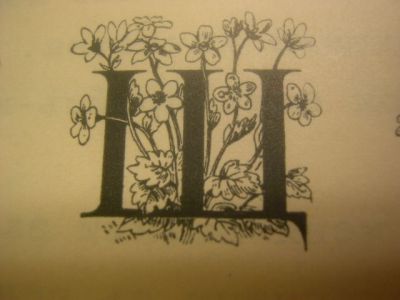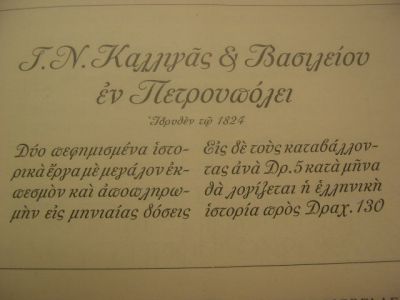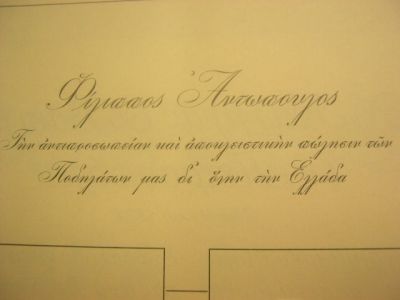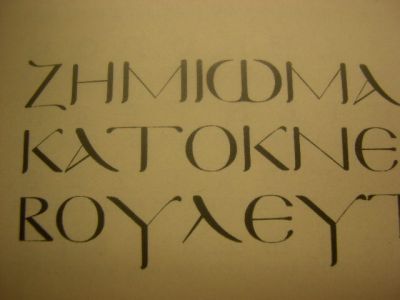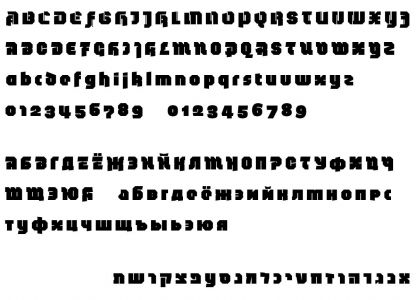
Griechische und kyrillische Schriften
ich bin auf der Suche nach kyrillischen und vorallem griechischen Schriften. In folgendem Bild seht ihr, welche Schriften ich für die jeweiligen Gruppen bereits gefunden habe:
(Ein größeres Bild gibt es hier.)
Eine griechische Egyptienne konnte ich nicht ausfindig machen. Aber die richtig großen Lücken klaffen bei den gebrochenen Schriften. Ganz besonders dürftig sieht es bei den griechischen Schriften aus. Leider habe ich noch keine Foundry eigens für griechische Schriften gefunden, so wie etwa ParaType für kyrillische Fonts.
Wenn jemand Foundries kennt, die auf griechische Schriften spezialisiert sind, lasst mich bitte nicht dumm sterben. Sollte jemand einen konkreten Font kennen, der eine Leerstelle auffüllen könnte, wäre ich für die Info noch tausendmal dankbarer.
Gibt es überhaupt sowas wie gebrochene griechische Schriften?
Historisch gesehen stellt sich diese Frage nicht nur für griechische, sondern auch für russische Schriften.
Ich habe gerade mal in meinen ältesten Schriftmuster-Büchern nachgeschaut von Schelter & Giesecke, der Bauerschen Gießerei und Klinkhardt: Es wurden sehr wohl griechische als auch russische Schriften angeboten, aber immer in Antiqua- oder Grotesk-Schnitten, auch als Schreibschriften. Aber nie als Gebrochene Schriften. Hebräische Schriften gab es übrigens auch. Und Aramäisch.
Ist nicht auch ein Widerspruch in einer Kombination Gebrochene Schrift <> Fremdsprachen-Zeichensatz? Nicht, daß es technisch nicht machbar (gewesen) wäre..
ja, es ist ein Widerspruch zwischen gebrochener und fremdsprachiger Schrift. Dennoch wurde er – zumindestens was das Kyrillische angeht – in der Vergangenheit bereits mehrfach aufgelöst; siehe die Beispiele aus meiner obigen Darstellung: »San Marco Cyr«, »Encient German Gothic« und »American Uncial«.
Gestern habe ich eine neuzeitliche Schrift gefunden (und mir selbst zu Ostern geschenkt), die ich als gebrochene Schrift klassifizieren würde. Sie zeigt, dass es nicht nur möglich ist, Kyrillisch sondern auch Hebräisch als gebrochene Schrift darzustellen:
229_kaas_1.jpgKaas von Thistype
Wenn das Kyrillische bereits als gebrochene Schrift wiedergegeben wurde, warum sollte das nicht auch für die griechische Schrift gehen? Leider finde ich jedoch keinerlei Beispiele und weiß auch nicht, wo ich recherchieren könnte. Daher nochmals mein Hilferuf!
ja, es ist ein Widerspruch zwischen gebrochener und fremdsprachiger Schrift. Dennoch wurde er – zumindestens was das Kyrillische angeht – in der Vergangenheit bereits mehrfach aufgelöst; siehe die Beispiele aus meiner obigen Darstellung: »San Marco Cyr«, »Encient German Gothic« und »American Uncial«.
Gestern habe ich eine neuzeitliche Schrift gefunden (und mir selbst zu Ostern geschenkt), die ich als gebrochene Schrift klassifizieren würde. Sie zeigt, dass es nicht nur möglich ist, Kyrillisch sondern auch Hebräisch als gebrochene Schrift darzustellen:
229_kaas_1.jpgKaas von Thistype
Wenn das Kyrillische bereits als gebrochene Schrift wiedergegeben wurde, warum sollte das nicht auch für die griechische Schrift gehen? Leider finde ich jedoch keinerlei Beispiele und weiß auch nicht, wo ich recherchieren könnte. Daher nochmals mein Hilferuf!
Ich kann gerade nur sehr schwer in Worte fassen, was ich an Deinen Beispielen als falsch empfinde. Und erhebe natürlich auch keinen Anspruch auf den Besitz einer allgemeinen Wahrheit.
Ich versuche es mit Beispielen aus anderen Bereichen, ja?
In Deutschland gibt es Indianer-Vereine. Die Leute treffen sich auf irgendwelchen Zeltplätzen, verkleiden sich als Indianer und verbringen ihre Freizeit im Stil der Indianer. Bis hin zur Sprache, die sie anpassen. Harmlos, tut niemandem weh. Hat aber mit der Realität der Indianer wohl nichts zu tun.
Mittlerweile finden auch "Mittelalter-Treffen" immer mehr Zulauf. Das ist eigentlich dasselbe. Nur spielen hier halt nicht die Vorstellungen Karl Mays eine Rolle, sondern die überlieferten Kino-Erinnerungen von Ivenhoe. Mit dem Leben im Mittelalter haben diese Treffen recht wenig gemein. Auch hier: Wem's Spaß macht..
In diesem Zusammenhang sehe ich auch die Darstellung von Kyrillisch oder Griechisch oder gar Hebräisch als Gebrochene Schrift. Nehmen wir letztere: In allen Hauptproben der großen Schriftgießereien zwischen 1900 und 1914 finden sich hebräische Schriften. Hätte irgendwer damals aus dem Zeitgeist heraus Sinn darin gesehen, Hebräisch als Fraktur darzustellen, wäre dies sicher ins Programm genommen worden. Ganz offensichtlich jedoch gab es danach überhaupt keine Nachfrage.
Kyrillische Schmuck-Initiale - von jedem kyrillischen Buchstaben eines, Format jeweils ca. 20 mm x 30 mm.
Meine Äußerung, daß es nur eine begrenzte Anzahl griechischer und russischer Schriften gibt, muß ich revidieren.
Im "Handbuch der Schriftarten" von Seemann, 1926, stehen 18 Seiten voll mit Mustern. Hier wegen des Platzes nur einige Wiedergaben. Bei wirklichem Interesse kann ich die Seiten kopieren und per Post zusenden.